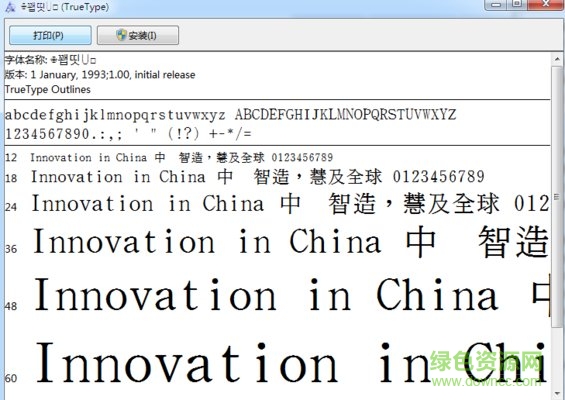
全真新中明字體是綠色資源網(wǎng)小編為需要進(jìn)行各類設(shè)計(jì)的朋友準(zhǔn)備的字體應(yīng)用,這款字體的行文結(jié)構(gòu)很優(yōu)美,擁有楷體的規(guī)定字體結(jié)構(gòu),感興趣的朋友歡迎下載使用!
全真新中明字體是一款風(fēng)格鮮明的電腦中文字體,橫細(xì)豎粗,筆畫輕盈,字形方正,靈秀中透露著大氣,美術(shù)設(shè)計(jì)、文字排版等方面都可以使用!